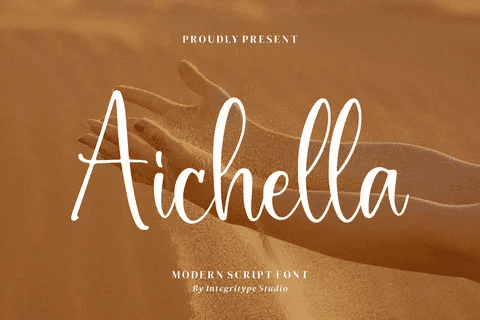
[Fontbundles] Aichella - Modern Script Font (2022)
Название: Aichella - Modern Script Font (2022)
[Fontbundles] Aichella - Modern Script Font (2022)
Aichella - Modern Script Font, от Integritype Studio, это премиальный каллиграфический шрифт, подходящий для любых проектов, таких как: логотипы, брендинговые проекты, дизайн домашней одежды, упаковка продуктов, кружки, цитаты, плакаты, сумки, футболки, обложки книг, именные карточки, пригласительные открытки, поздравительные открытки, этикетки, фотографии, водяные знаки, специальные мероприятия, и все другие роскошные проекты, которым нужен премиальный фирменный вкус.